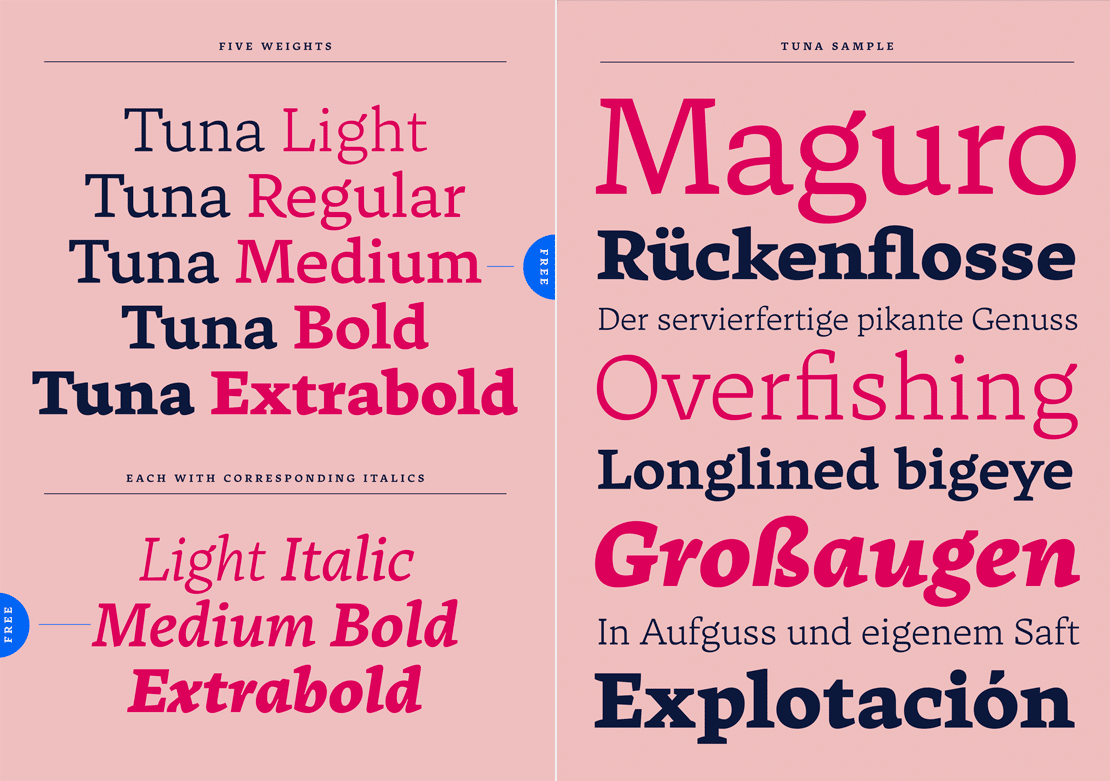
Neue Schrift »Tuna«
Nach 3 Jahren Entwicklungszeit ist die Schriftfamilie »Tuna« von Alex Rütten und Felix Braden erschienen. Sie wurde für den crossmedialen Einsatz am Bildschirm und auf Papier optimiert.
»Tuna« ist eine lebhafte, zeitgenössische Fließtextschrift mit kräftigen Serifen. Das Design basiert auf Formen, die für unterschiedliche Wiedergabebedingungen konzipiert wurden. Die Schrift wurde so gestaltet, dass sich markante Elemente und charakteristische Details erst bei der Verwendung in großen Schriftgraden zeigen. So kann »Tuna« im Web und im Druck gleichermaßen eine gute Figur machen.
Die Familie beinhaltet 10 aufeinander abgestimmte Schnitte. Mit Kapitälchen, verschiedenen Zahlensystemen und umfangreicher Sprachunterstützung kommt sie auf über 700 Glyphen.